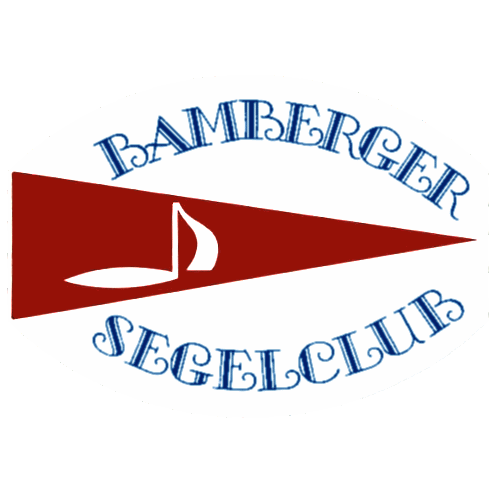
Suche Schriftart vom Vereinslogo (Bamberger Segelclub)
ich suche die Schriftart unseres Logos vom Bamberger Segelclub. Das Logo wurde vermutlich in den 1970er Jahren erstellt. Es existiert meines Wissens nur eine Bilddatei (.png). Hat jemand eine Idee?
Das mit der Note habe ich mich tatsächlich auch gefragt! Aber die grundsätzliche Gestaltung Eures Logos war ja hier nicht zur Diskussion gestellt – und der geschätzte Kollege bertel hat die richtige Schrift auch schon für Dich gefunden. Insofern frage ich Dich nicht, ob Ihr das Logo vielleicht überarbeiten möchtet (Berufskrankheit – Gestalter sehen immer Optimierungsmöglichkeiten! ;-))  sondern wünsche einfach ein schönes Wochenende (zum Segeln ja leider in unseren Breiten noch ein bisschen zu frisch …). :huhu:
Aber die grundsätzliche Gestaltung Eures Logos war ja hier nicht zur Diskussion gestellt
Hat mich nämlich sofort gereizt, das Logo! Das könnte man sicherlich noch ein klein wenig schöner machen, aaaaber: Das war ja (leider) nicht gefragt. Und deshalb hatte ich mir direkt selber das Wort verboten, denn die Schrift hattest Du ja schon gefunden und damit die Frage wunderbar beantwortet. ;-)
vielen Dank für eure Unterstützung. Die stilisierte Note steht für die Bamberger Symphoniker, von denen einige Gründungsmitglieder des Segelclubs waren/sind. Und der rote Wimpel für den Segelsport.
Überarbeiten?! Ja, ist auch mein erster und immer wiederkehrender Impuls, wenn ich das Logo sehe. In erster Linie die Schrift, die finde ich nicht passend für diesen Zweck. Mal schauen, wann ich das mal vorsichtig angehe und dem Vorstand diesbezüglich einen Vorschlag unterbreite.
ach spannend – dann hat das »Notenboot« ja tatsächlich seine Berechtigung, Rätsel gelöst! :-D
Ich kann mir gut vorstellen, das es Einige aus der Typo-/Gestaltungsbranche reizt, das Logo zu ... . Und ich frage mich, was wären deine Ideen, "es ein klein wenig schöner" zu machen? Aber bevor ich da einsteige, will ich erst den Vorstand befragen.
Hat mich nämlich sofort gereizt, das Logo! Das könnte man sicherlich noch ein klein wenig schöner machen, aaaaber: Das war ja (leider) nicht gefragt.
ich muss auch die richtigen Worte finden, soll es eine Weiterentwicklung des Logos, über einen Anstoß von mir, geben. Mal sehen, ob es gelingt.
Wobei ich gerade die Schrift knuffig finde: Da habe ich gleich ein Bild vor Augen mit jungen Herren in grobgestreiften Sakkos und Kreissägen auf dem Kopf, die fröhlich scherzend in ihren Optimisten übern See schippern ...
Aber so seid ihr wahrscheinlich nicht, oder :-D
Die Schrift find ich auch gut. Die Komposition mit Keil und Note (das waren meine ersten Eindrücke) aber eher nicht so.
Wobei ich gerade die Schrift knuffig finde: Da habe ich gleich ein Bild vor Augen mit jungen Herren in grobgestreiften Sakkos und Kreissägen auf dem Kopf, die fröhlich scherzend in ihren Optimisten übern See schippern ...
So etwas filigranes für ein Logo wäre uns in der Ausbildung um die Ohren geflogen. Aber irgendwie passend zur Zielgruppe finde ich es auch.
Die Schrift macht wirklich gute Laune, mit all ihren kleinen fröhlichen Wellen. :-D
Dennoch würde ich für ein Segelclublogo bei der Schrift wohl etwas weniger Schnörkel bevorzugen. Und dann eine Bildmarke entwickeln, die besser mit der Formensprache der Schrift harmoniert als das derzeit der Fall ist. Beziehungsweise würde ich im Normalfall ohnehin zuerst die Bildmarke entwickeln und dann im Anschluss die passende Schrift dazu setzen. Oooooder einen individuellen Schriftzug zeichnen und ohne Bildmarke auskommen … und so. Irgendwie. Würde ich. Wenn ich dürfte. ;-)